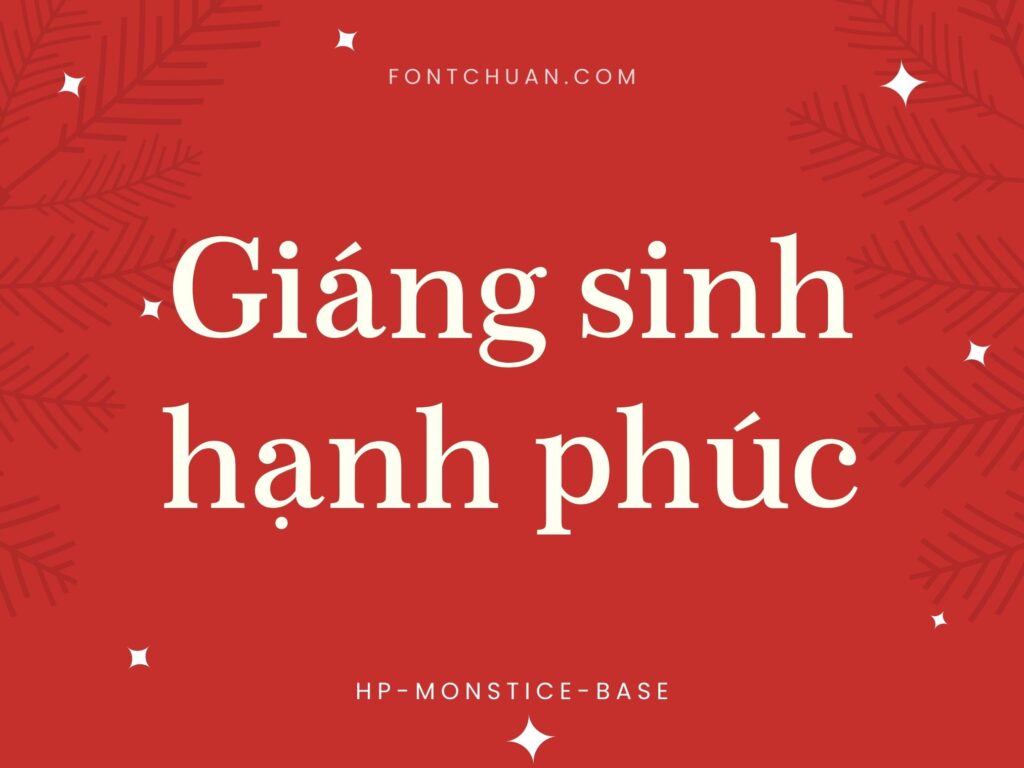
Font Hp Monstice Trọn Bộ Việt Hóa
Monstice là một bộ Font Serif trang trí được thiết kế bởi Cucu Supriyadi và phát hành bởi Seventh Imperium. Bộ font bao gồm 7 phong cách: Base, Emboss, Engraved, Hatched, Inline, Shadow và Element, cho phép sự linh hoạt trong thiết kế. Với thiết kế tinh tế và chi tiết, Monstice mang lại vẻ đẹp cổ điển và sang trọng, phù hợp cho các dự án yêu cầu sự nổi bật và đẳng cấp. Font này đã được Việt hóa bởi Mộc Hạ – MTD, hỗ trợ tiếng Việt và nhiều ngôn ngữ khác, được sưu tầm và đăng bởi thành viên của Font Chuẩn.
Không chỉ phù hợp với các thiết kế mang phong cách cổ điển, Monstice còn có thể được xem là một Font chữ ẩm thực lý tưởng nhờ đường nét mềm mại, thanh thoát và khả năng tạo cảm giác sang trọng, tinh tế — rất phù hợp cho thiết kế menu, logo nhà hàng, thương hiệu thực phẩm hoặc bao bì đồ uống cao cấp.
Monstice có các nét chữ trang trí độc đáo, với độ tương phản cao và các chi tiết phức tạp, tạo nên sự cuốn hút và ấn tượng. Font này lý tưởng cho các thiết kế bìa sách, poster, bao bì sản phẩm, tiêu đề và nhận diện thương hiệu. Các ngành nghề như quảng cáo, thiệp cưới, bất động sản và ẩm thực có thể tận dụng hiệu quả font này. Ngoài ra, Monstice cũng thích hợp cho các sự kiện như Tết, lễ hội, ngày Nhà giáo, Valentine và có thể sử dụng như một Font chữ Giáng Sinh để trang trí thiệp, poster hay banner mùa lễ hội, mang đến không khí rộn ràng, ấm áp và vui tươi cho các sản phẩm thiết kế.